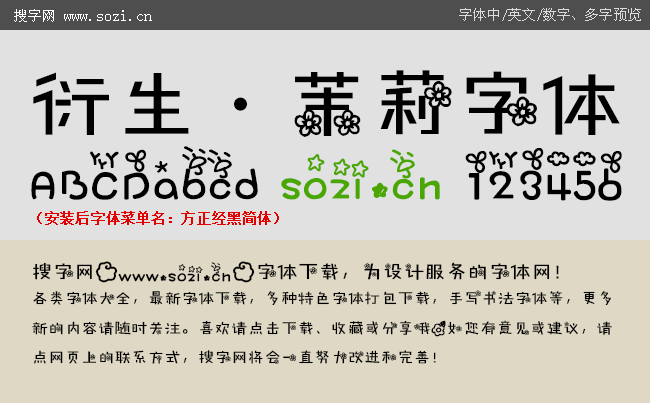
衍生·茉莉字體
搜字網(wǎng)給大家提供一款很可愛的手機(jī)中文字體下載。字體名叫衍生·茉莉字體,這款手機(jī)字體是以方正經(jīng)黑字體為原形,筆畫間插入了可愛的卡通圖案。方正經(jīng)黑體靈巧可愛,充滿趣味性,是一款非?蓯鄣目ㄍㄗ煮w,特別適合喜歡手機(jī)字體個(gè)性一些的朋友在手機(jī)上安裝使用。